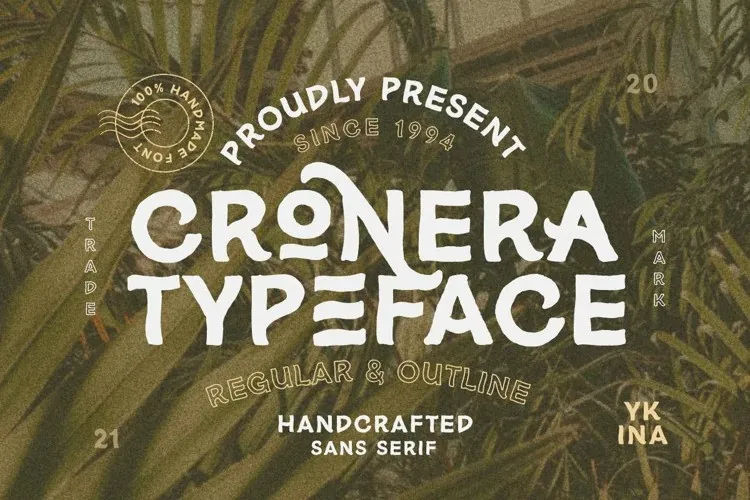
A “Cronera Font” é uma opção ideal para quem busca estilo sem compromisso, combinando características únicas de uma escrita manuscrita com a textura autêntica e o visual descontraído de um estilista vintage. Cada caractere desta fonte em display tem uma aparência retrô encantadora, perfeitamente adaptável para criar capas de livros com toque retro ou design personalizado para camisetas criativas. Além disso, sua versão contorna oferece flexibilidade suficiente para se adequar a uma ampla variedade de projetos que vão desde slogans a marcas únicos. Com suporte para múltiplas línguas, esta fonte irá tornar seu próximo projeto ainda mais diversificado e sofisticado. Se você está procurando por uma maneira criativa de expressar sua personalidade ou marca através de um design visual chamativo, a “Cronera Font” pode ser a solução perfeita para seus anseios. Através da “Cronera Font”, transforme suas ideias em arte viva e única no formato digital.